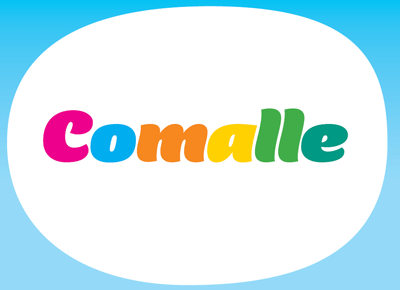
Font für Mädels
eine Schrift für Mädchenspielzeug (als Logo). Überlegungen:
Weitere Vorschläge und eine Diskussion sind erwünscht.
bist du bei 4-jährigen oder 40-jährigen Mädels?
Lustiger Verein hier. :D Wir reden natürlich von Puppen, Schmuck, Pferdchen und so weiter.
Möchte trotzdem einen etwas akademischeren Anspruch mit einfließen lassen, auch wenn diese Dinger meistens Arsch aussehen.
Die Tekton habe ich gerade entdeckt, die könnte doch vielleicht was sein, oder? Comalle wäre eigentlich ideal, sieht aber schon sehr nach 70er aus, finde ich.
Wenn ich so meine 5-Jährige Tochter anschau, die ich grad ins Bett gesungen hab: Es muss rosa sein, Schleifchen haben, Feenflügel, Pferde, noch besser Einhörner. Schrift: Total egal. Mit Schrift richtest du in deiner Zielgruppe grad mal gar nix aus. Gestaltung, Farb- und Formenwelt müssen passen.
FINGER WEG VON DER TEKTON!
comalle könnte ich mir gut vorstellen, kommt aber auch auf die wortmarke an
und was du daraus machst (in bezug auf die restliche gestaltung und logo)
denke auch daran das evtl die eltern das spielzeug kaufen und nicht die kinder,
evtl. reicht es schon bei der verpackung in die vollen zu gehen und das logo eher
dezent und professionell wirken zu lassen.
Die Tekton würde ich auch nicht nehmen. Wie wäre es denn mit der Cocon? Ansonsten fallen mir noch die Wendy oder die Jelly Bean ein. Inagur ist auch interessant. :)
Aber ist das wirklich die Zielgruppe? Wenn ich mich in meinem Umfeld so umschaue, kaufen die Großeltern mit Abstand das meiste (und teuerste) Kinderspielzeug. Das wären dann also Bildungsbürger so ab 55 (die lassen sich mit dem Kinderkriegen länger Zeit, werden dann also auch später Großeltern), Angehörige bildungsferner Schichten ab 35 und was so dazwischen liegt.
Irgendwie bin ich bei der Comalle hängen geblieben. Gibt es eine (kostenlose) Alternative?
So richtig formale? Nein. Es gibt da aber paar recht brauchbare Fettmarkerschriften:
Market von Unbekannt: http://www.abstractfonts.com/font/211
Scratch von Sir Speedy: http://www.abstractfonts.com/font/13263
Yard Sale von Harald Lohner: http://www.abstractfonts.com/font/13400
und dann noch was ganz anderes:
Dummies von RudynFluffy : http://www.abstractfonts.com/font/1846
Ps: Der Erwachsenenspielzeugladen (für die reiferen Mädchen) Beate Use hat die IIRC fette Gill. :mrgreen:
Hm, dann haben wir verschiedene Umfelder. In meinem haben die Eltern ziemlich den Daumen drauf, was ins Kinderzimmer kommt und was nicht. Großeltern sprechen sich idR mit den Eltern ab, damit es keinen Ärger gibt. Die Entscheidung wird aber sehr stark von den Kindern beeinflusst, die was sehen und unbedingt haben wollen. Wenn es passt, wird es evtl. dann auch angeschafft. Kinder gehen da aber eher nach Inhalten ran (Feen, rosa, Einhörner bei den Mädels), Eltern ebenso ("pädagogisch wertvoll", ohne Weichmacher etc.) Dass jemand einen Font oder ein Logo und nicht den Gesamteindruck wahrnimmt, kenne ich dabei nicht.
Die hältst du für "recht brauchbar" für Mädelsspielzeug? Oh weia, damit liegst du komplett daneben.
Ich habe geschrieben: „brauchbare Fettmarkerschriften”. Die Zuordnung zur Zielgruppe habe ich ausgelassen. Ich habe mich nur an der Frage nach Substitution orientiert. Bzgl. der geltenden Vorurteile bzgl. des geschlechtsspezifischen Geschmacks enthalte ich mich jeder Aussage, mangels eigenem Geschmack.
Aber wenn schon „mädchenhaft”: ZiptyDo (kommerziell), ZiggyZoe (Freeware) :P